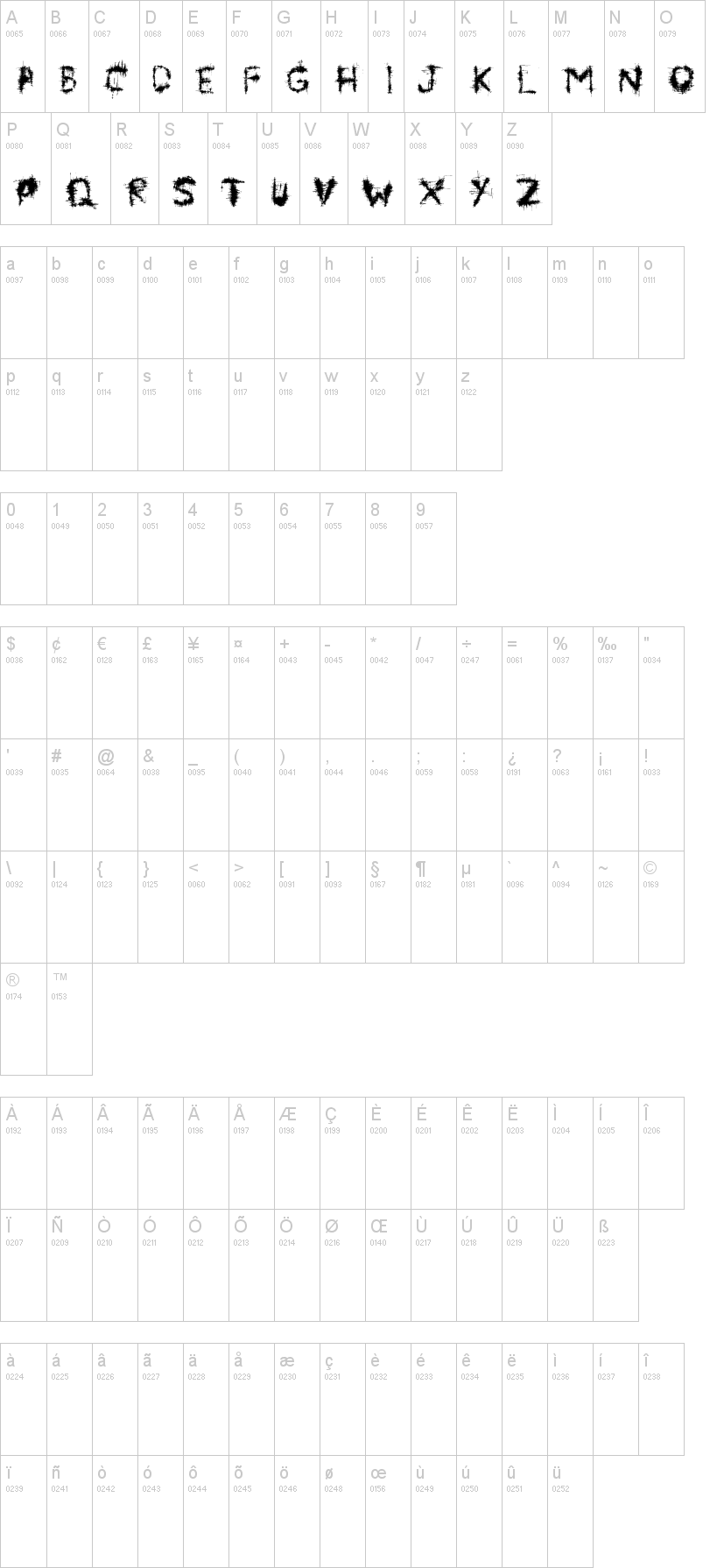
Symbiote 字体是一款多功能的字体,它可以让您轻松地创建出漂亮的文字效果。它具有许多灵活的特性,可以调整字体的大小,字形,字间距,粗细,字母间距等,以及支持多种语言。它还具有不同的字体风格,可以满足您的各种设计需求。它的设计精美,可以让您的文字更加突出,令人印象深刻。内容介绍
Symbiote是一款非常不错的手写艺术字体,具有很好的视觉感,适合于文化类的宣传设计、商业类品牌的广告和产品包装设计以及个性化文字排版等较多场景。